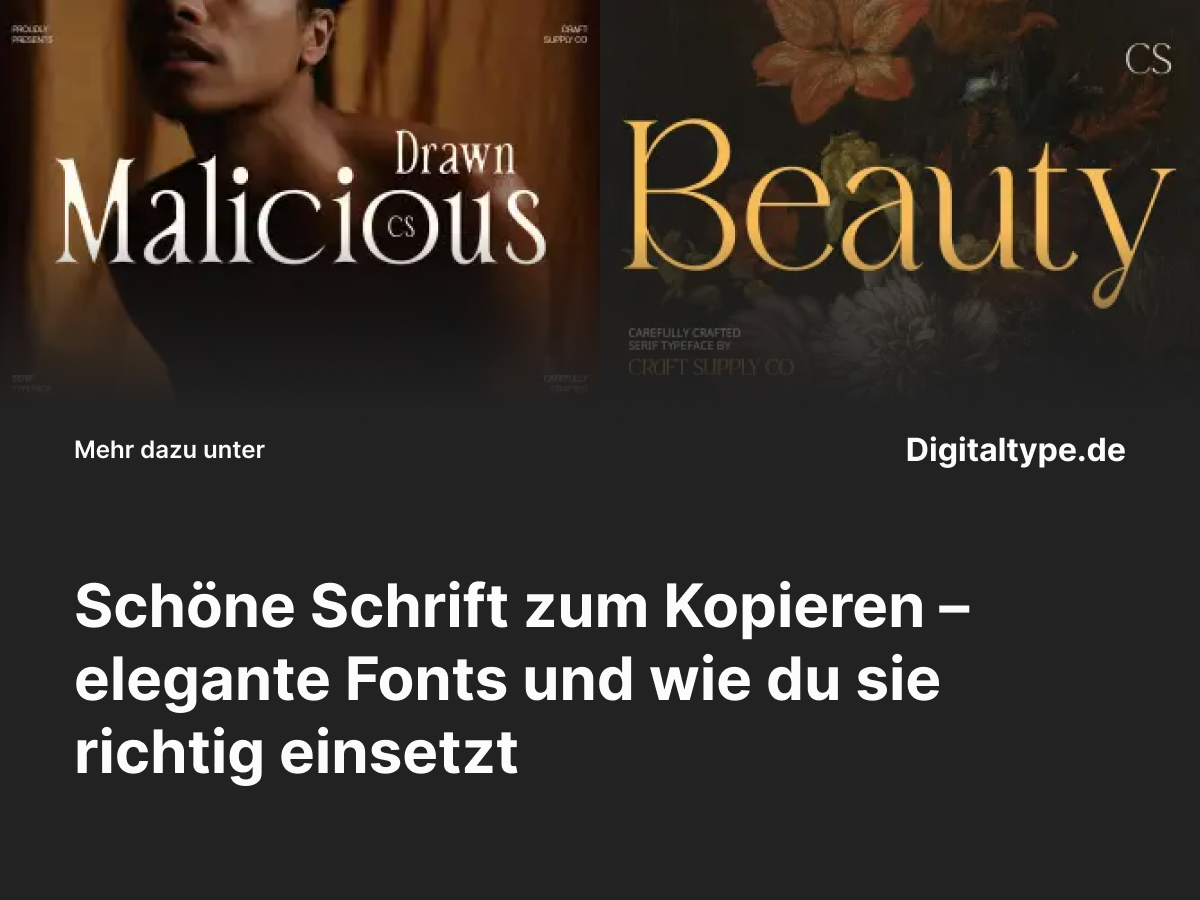
Eine schöne Schrift zum Kopieren kann dein Layout sofort aufwerten: sie verleiht Social-Media-Posts, Einladungen, Logos oder Produktverpackungen Persönlichkeit und Stil. Doch nicht jede attraktive Schrift eignet sich eins zu eins für alle Projekte. In diesem Artikel erklären wir, was eine „schöne Schrift zum Kopieren“ ausmacht, wie du sie korrekt und legal übernimmst, welche Gestaltungsregeln du beachten solltest und präsentieren sechs sorgfältig ausgewählte Fonts als praktische Alternativen.
Was bedeutet „schöne Schrift zum Kopieren“?
Mit dem Ausdruck schöne Schrift zum Kopieren sind in der Regel dekorative, oft script- oder handschriftlich wirkende Fonts gemeint, die sich leicht in Texte einfügen lassen — etwa für Zitate, Headlines oder Signaturen. „Kopieren“ heißt hier nicht unbedingt, dass du die Schrift ungeprüft von einer Website kopierst; gemeint ist vielmehr das schnelle Übernehmen eines Stils oder die direkte Nutzung einer verfügbaren Fontdatei. Wichtig ist: immer auf Lizenz und Nutzungsrechte achten, bevor du eine Schrift kommerziell einsetzt.
Wann du solche Schriften verwenden solltest
- Für Social-Media-Grafiken und Storys, die Aufmerksamkeit erregen sollen.
- Bei Einladungen, Save-the-Date-Karten oder Hochzeitspapeterie, wo Persönlichkeit gefragt ist.
- In Logos oder Wortmarken, wenn eine handschriftliche Note zur Markenidentität passt.
- Als Akzent in Editorials: kurze Zitate, Hervorhebungen, Section-Headlines.
Solche Schriften funktionieren am besten punktuell — als Akzent und nicht im langen Fließtext. Sie erzeugen Emotion, stehen aber oft im Kontrast zur Lesbarkeit; deshalb sollten sie sparsam und bewusst eingesetzt werden.
Gestaltungsregeln: So nutzt du schöne Schriften effektiv
Damit eine dekorative Schrift ihr volles Potenzial entfaltet, beachte diese praktischen Gestaltungsregeln:
- Kontrast schaffen: Kombiniere eine verspielte Script-Font mit einer neutralen Sans-Serif für Fließtext.
- Lesbarkeit prüfen: Teste in unterschiedlichen Größen und auf Mobilgeräten — manche feinen Striche verlieren sich bei kleiner Darstellung.
- Weißraum geben: Handschriftliche Fonts benötigen mehr Luft; erhöhe Zeilenhöhe und Buchstabenabstand bei Bedarf.
- Farbkontrast: Hell auf hell wirkt schnell unsauber — klare Kontraste verbessern die Wirkung.
- Nur wenige Schriftschnitte: Nutze maximal zwei bis drei Schriften pro Layout, um Ruhe zu bewahren.
Die 6 schönsten Schriften zum Kopieren (Alternativen)
Nachfolgend sechs stilvolle Fonts, die sich hervorragend als schöne Schrift zum Kopieren eignen. Jede Beschreibung erklärt kurz Stärke, Einsatzbereich und Charakter.
1. CS Malicious Drawn Font
CS Malicious ist eine ausdrucksstarke, gezeichnete Schrift mit markantem Charakter. Sie eignet sich für plakative Headlines, Poster und Coverdesigns, bei denen ein leicht rauer, handgemachter Look gewünscht ist. Robust genug für große Formate, hat sie genug Persönlichkeit, um allein zu stehen.
2. CS Beauty Stylish Font
CS Beauty ist elegant und modisch, ideal für feminine Branding-Projekte, Kosmetik- oder Modevisuals. Die Formen sind luftig und fein ausgearbeitet, wodurch sie sich gut für Logos, Produktverpackungen und Social-Media-Grafiken eignet, die einen stilvollen Eindruck erzielen sollen.
3. CS Hailey Script Font
CS Hailey liefert eine fließende, kalligrafische Handschrift mit natürlichem Schwung. Sie funktioniert hervorragend als Signatur-Font, für Einladungen oder emotionale Zitate. Achte bei Verwendung in kleinen Größen auf ausreichend Strichstärke für gute Lesbarkeit.
4. CS Admire Script Font
CS Admire steht für klassische Eleganz und ausgewogene Proportionen. Diese Script-Schrift eignet sich für hochwertige Editorials, Magazine und Branding-Projekte, in denen Zeitlosigkeit und Stil im Vordergrund stehen.
5. CS Asbury Classic Font
CS Asbury ist eine klassische Serifenschrift, die sich als ruhiger Gegenpol zu dekorativen Scripts eignet. Nutze sie für Fließtext, Begleittexte oder Subheadlines, um Struktur und Lesbarkeit zu gewährleisten, ohne auf Eleganz zu verzichten.
6. CS Adelina Script Font
CS Adelina bietet weiche, natürliche Schwünge und eine warme Handschrift-Ästhetik. Sie ist besonders geeignet für Branding, handwerklich wirkende Verpackungen und Projekte mit persönlicher, freundlicher Ausstrahlung.
Fazit
Eine schöne Schrift zum Kopieren gibt dir schnellen Zugriff auf typografischen Stil und Ausdruck — vorausgesetzt, du achtest auf Lizenz und Lesbarkeit. Nutze dekorative Fonts gezielt als Akzent, kombiniere sie mit neutralen Begleitfonts und teste die Wirkung in verschiedenen Größen. Die sechs vorgestellten Alternativen bieten dir solide Optionen für unterschiedliche Stimmungen: von elegant über handschriftlich bis markant.